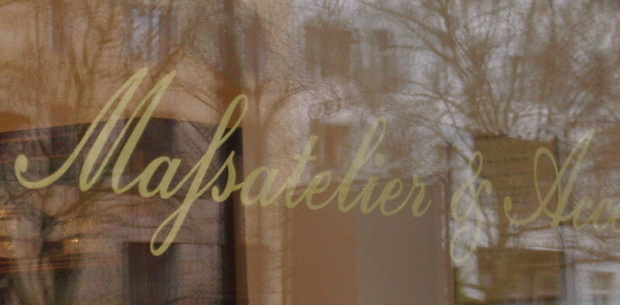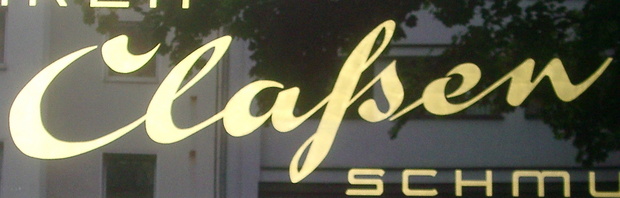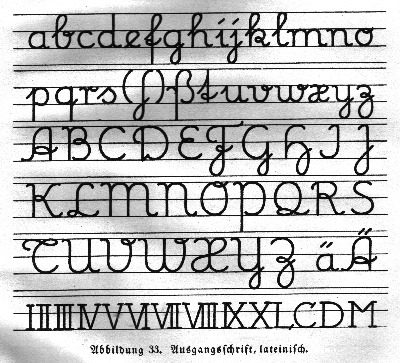
Lateinische Schreibschrift im 19. und 20. Jhdt.
ich suche Informationen zu den Lateinischen Schreibschriften mit der Form des langen-s wie in den Beispielen unten abgebildet.
Bei Maſsatelier oder Claſsen. Bei der lateinischen Schulausgangsschrift von Sütterlin ist die untere Schlaufe vorhanden. Bei der Deutschen Normalschrift (per Erlass 1941) ist das lange-ſ schon nicht mehr dabei. Vielleicht kennt auch jemand so eine Schrift mit dem langen-s, das dem h in der Deutschen Kurrentschrift zum Verwechseln ähnlich sieht.
Allerdings fehlt bei dieser Schrift die Oberschlaufe (wie bei der lateinischen Sütterlin), so dass das lange-s noch gut zu erkennen ist.
Vielleicht findet sich noch eine ähnlichere mit Oberschlaufe?
diese Ausformung des langen-s entstand im 17. Jhdt. Muss sich aber wohl bi zum 20. Jhdt. gehalten haben.
Wie wären denn sonst die Schaufensterbeschriftungen zu erklären?
Kennt jemand diese lateinische Schreibschrift?